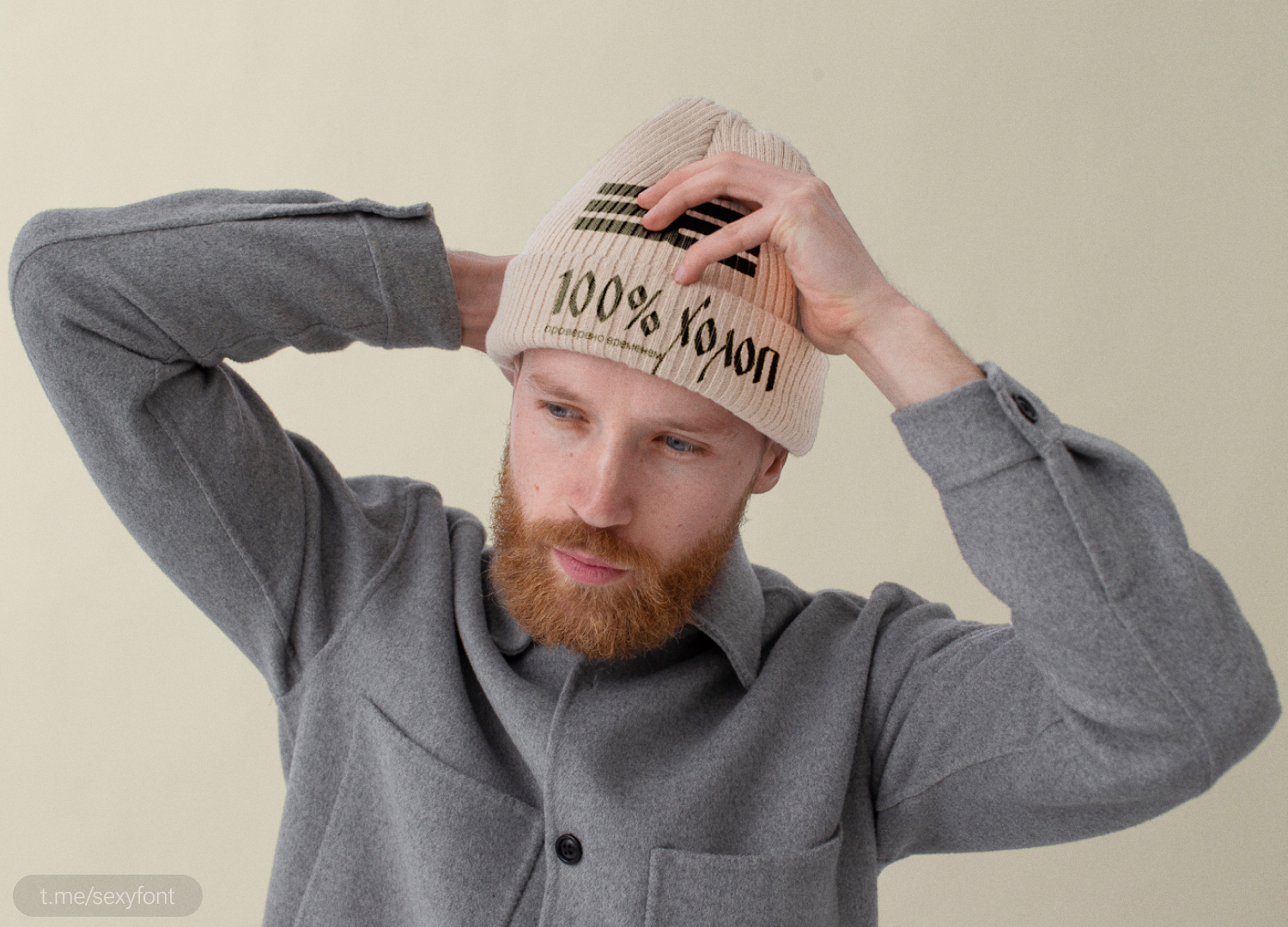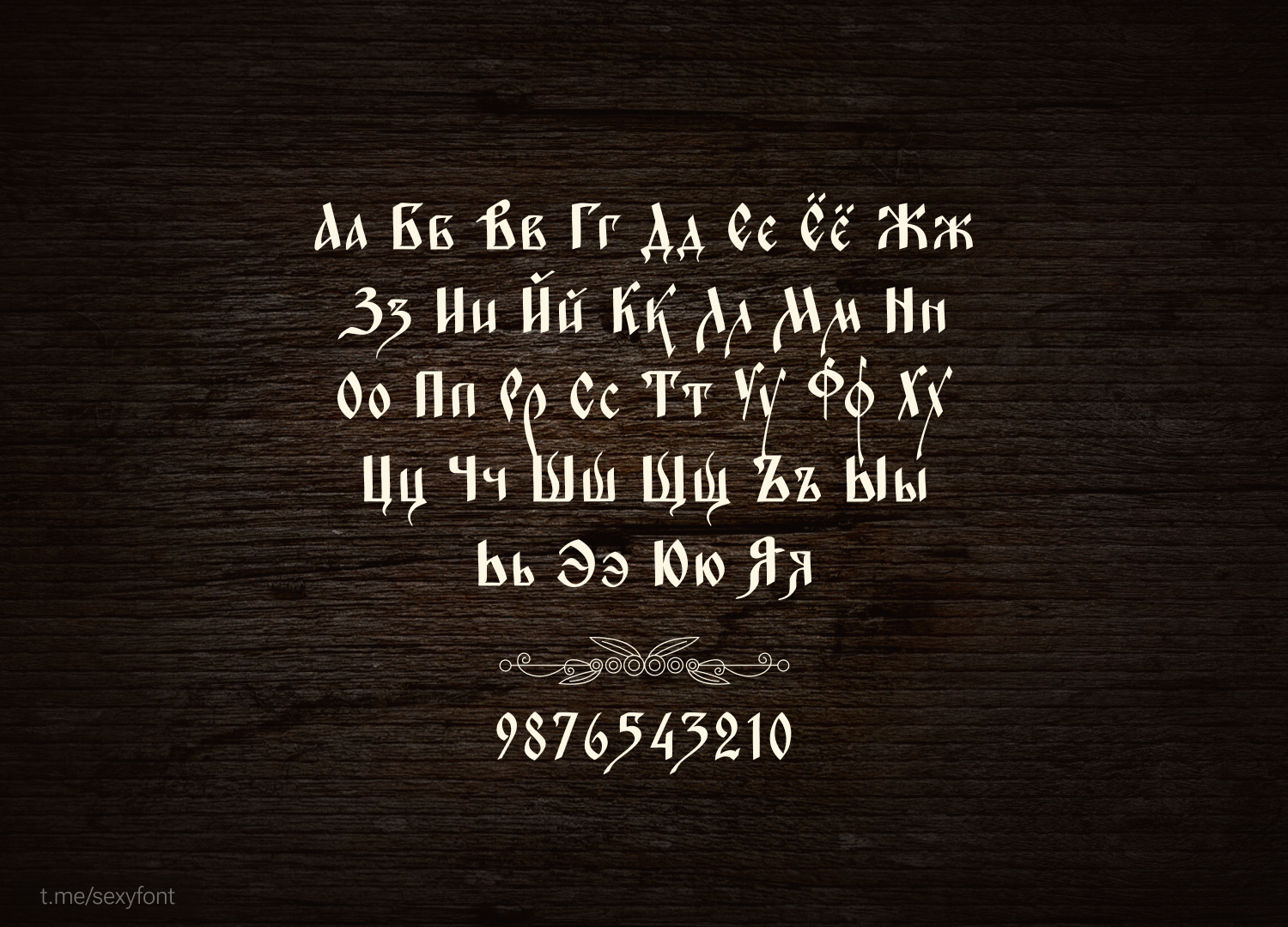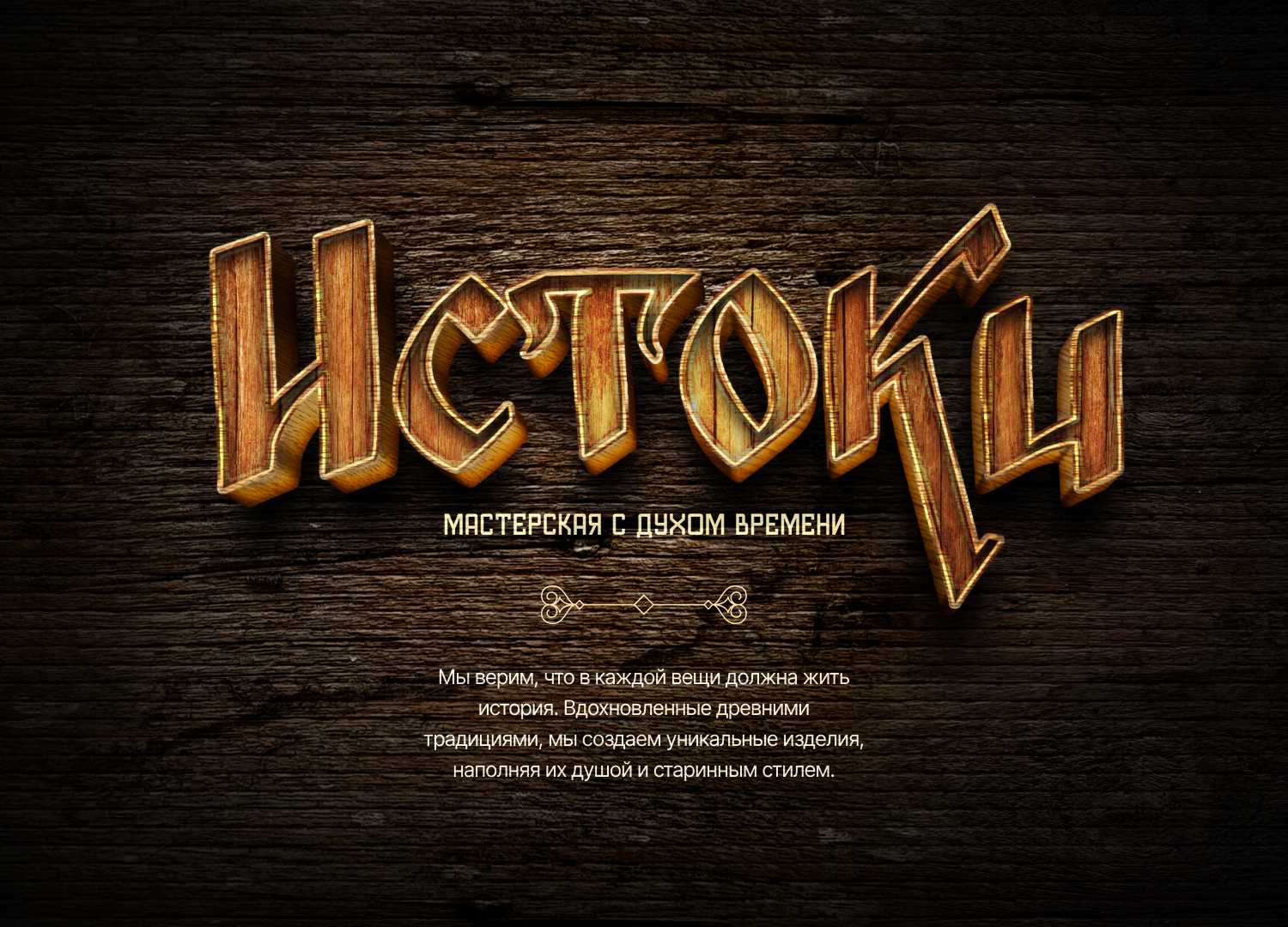
Шрифт «Извод»
Шрифт «Извод» в старославянском стиле. От Дмитрия Тектова в коллобарации с Максимом Кулешовым . Спасибо авторам за шрифт. А нам за презентацию